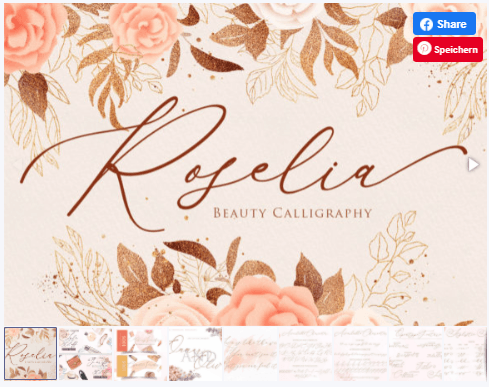
Roselia Font
Roselia - красивый и изысканный шрифт. Он имеет стильный, элегантный и современный вид, который можно использовать для логотипов, брендинга, приглашений, канцелярских товаров, свадебного дизайна, сообщений в социальных сетях и многого другого! Roselia закодирована PUA, что означает, что вы можете легко получить доступ ко всем глифам и росчеркам!